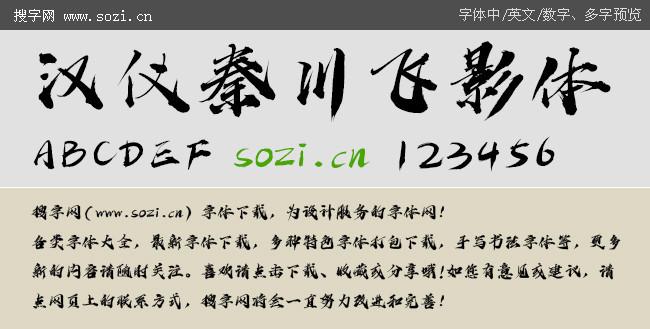
漢儀秦川飛影體
搜字網(wǎng)提供一款漢儀秦川飛影體中文字體下載,漢儀秦川飛影體是一款手寫風(fēng)格的書法字體,帶有古典氣息,外形和手書體有點(diǎn)像,線條張揚(yáng)肆意,富有動(dòng)勢(shì),特征鮮明,能夠適用于藝術(shù)設(shè)計(jì)、包裝印刷、海報(bào)設(shè)計(jì)、圖形設(shè)計(jì)等領(lǐng)域。(如需要商用請(qǐng)聯(lián)系漢儀字庫(kù)購(gòu)買版權(quán))